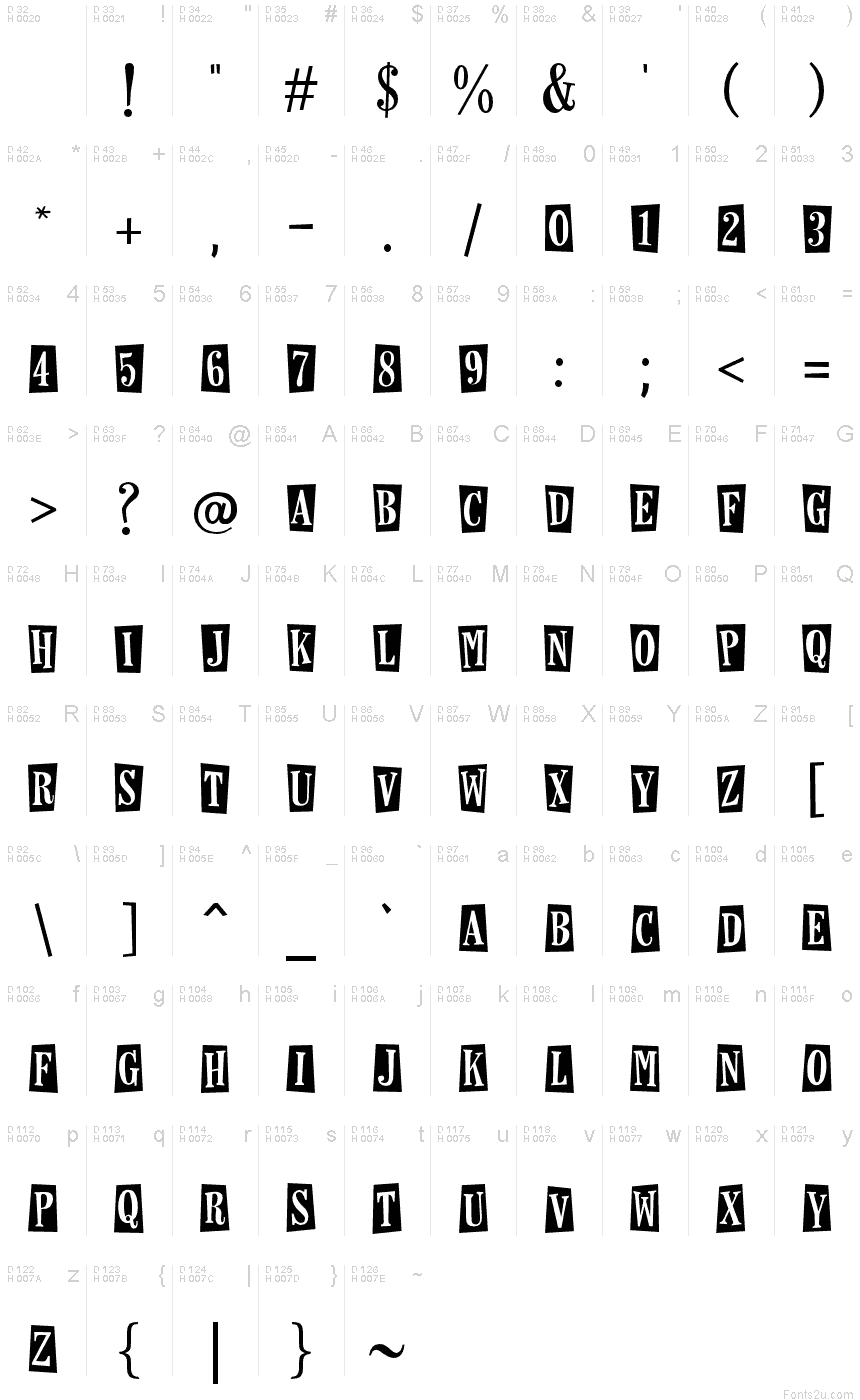
Horseshoes And Lemonade
Horseshoes and Lemonade od Lauren Ashpole je bezplatné dekorativní display písmo s hravým nádechem papírové koláže. Každé písmeno sedí ve vlastním zkoseném černém bloku, jako ručně vyřezávané cedule na letním jarmarku, a mísí robustní tvary typu slab s neotřelými, zakřivenými detaily. Výsledek působí odvážně, výrazně a v tom nejlepším slova smyslu trochu „mimo mísu“.
S Horseshoes and Lemonade vaše nadpisy na plakátech, pozvánkách na dětské akce, cedulích k limonádovým stánkům, vizuálech pro řemeslné trhy, obálkách knih či veselých příspěvcích na sociálních sítích okamžitě upoutají pozornost. Toto bezplatné písmo nejlépe vynikne velké a výrazné; v menších velikostech ho kombinujte s jednoduchým geometrickým bezpatkovým písmem, aby vaše layouty zůstaly čitelné a zábavné.